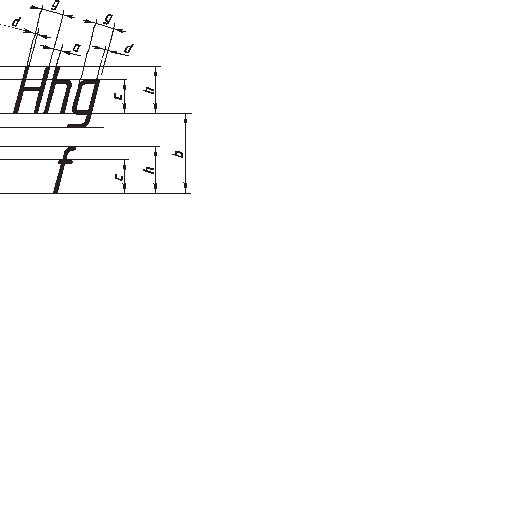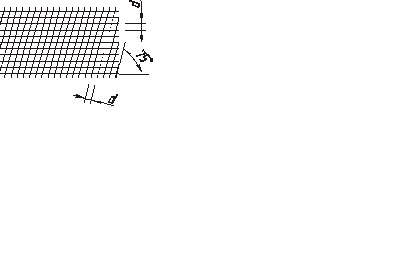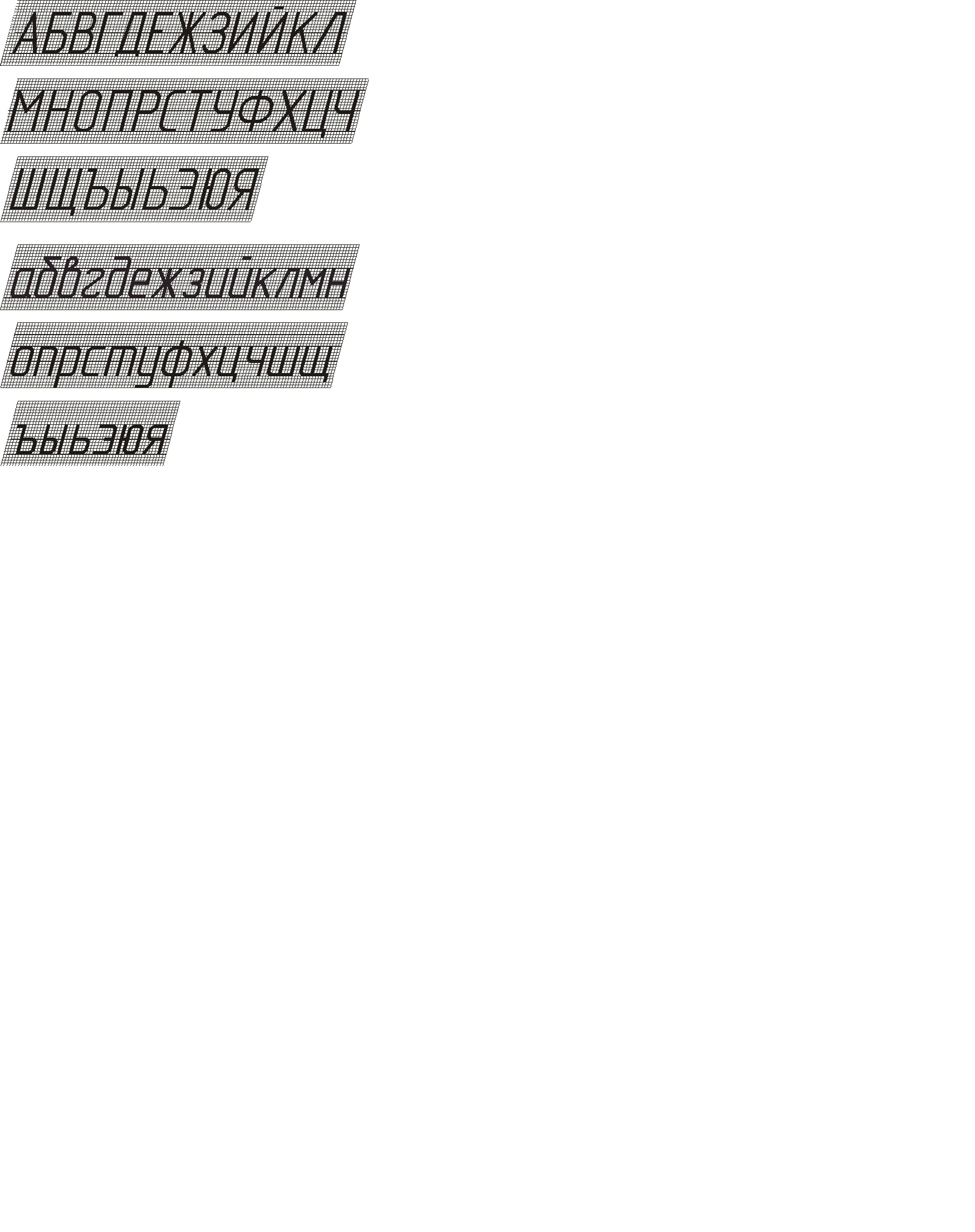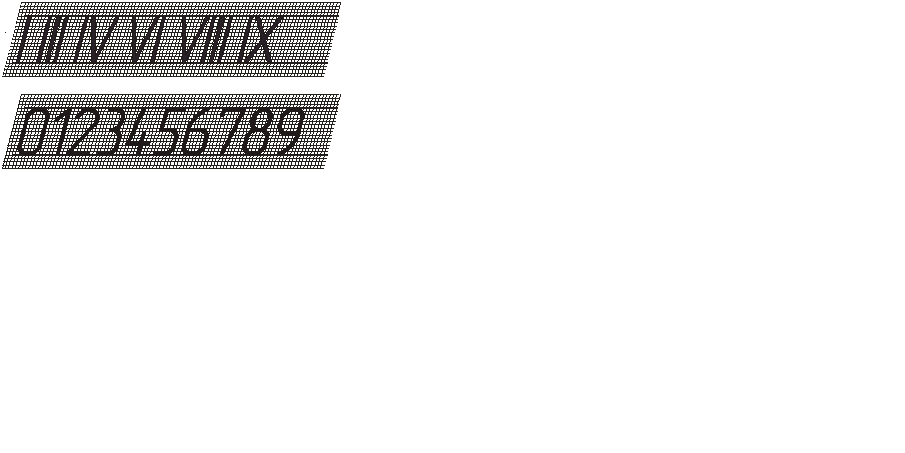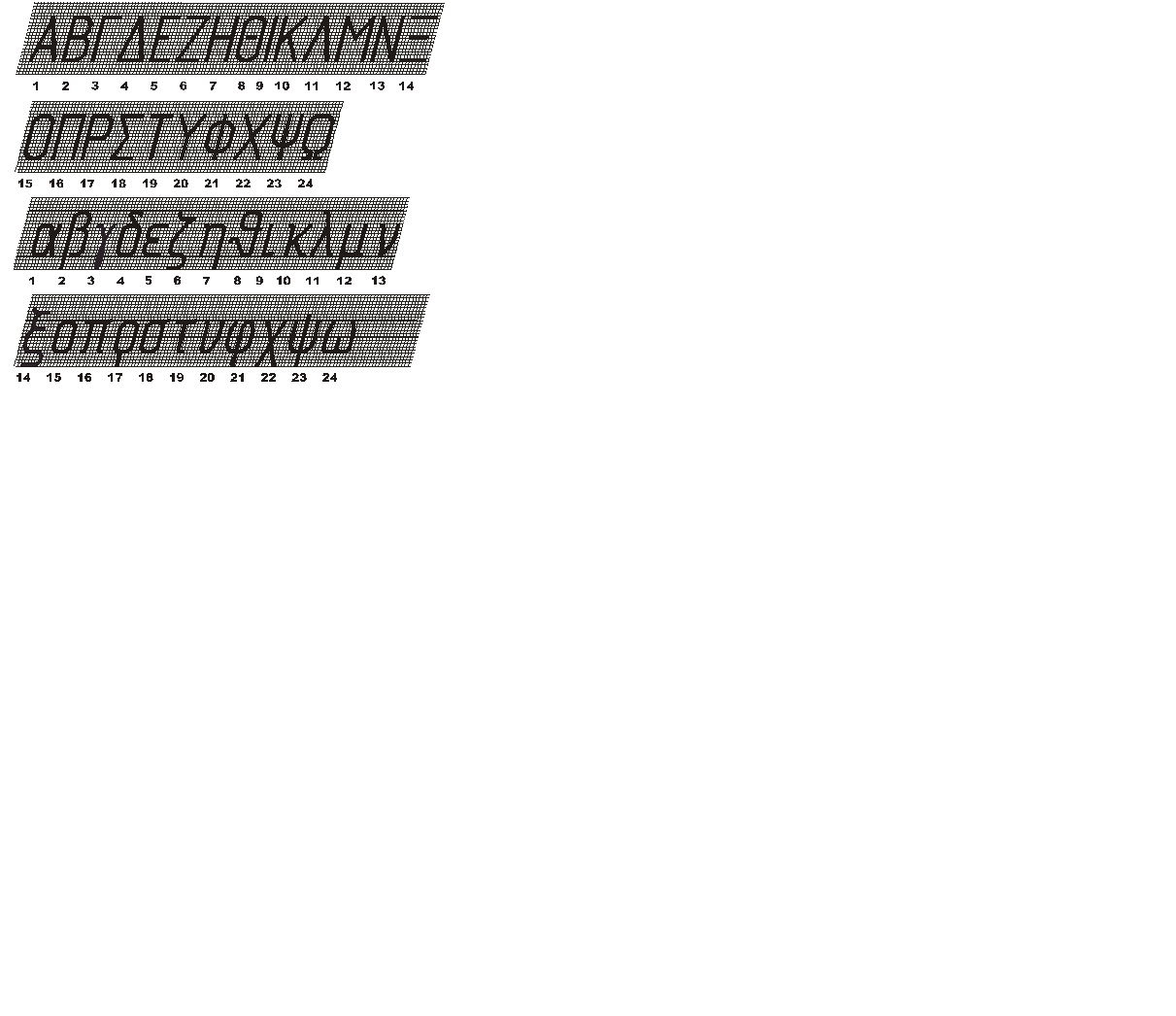
Шрифты чертежные. Чертежи выполняются на листах размерами, установленными ГОСТ 2
Все надписи на чертежах должны быть выполнены чертежным шрифтом. ГОСТ 2.304-81 устанавливает два типа шрифта: тип А и тип Б, с наклоном и без наклона. В настоящем пособии подробно рассмотрен шрифт тип А с наклоном 75° и параметрами, приведенными в таблице 4. Размер шрифта h – величина, определенная высотой прописных букв в миллиметрах. Высота прописных букв h измеряется перпендикулярно к основанию строки. Высота строчных букв c определяется из отношения их высоты (без отростков k) к размеру шрифта h, например, с = 7/10h (рисунки 1 и 2) Ширина буквы g – наибольшая ширина буквы, измеренная в соответствии с рисунками 1 и 2, определяется по отношению к размеру шрифта h, например, g=6/10h, или по отношению к толщине линии шрифта d, например, g = 6d. Толщина линии шрифта d – толщина, определяемая в зависимости от типа и высоты шрифта.
Рисунок 1
Вспомогательная сетка – сетка образованная вспомогательными линиями, в которые вписываются буквы. Шаг вспомогательных линий сетки определяется в зависимости от толщины линии шрифта d (рисунок 2).
Рисунок 2
Таблица 4 - Шрифт типа А (d= h/14) с наклоном
Примечания: 1 Расстояние a между буквами, соседние линии которых не параллельны между собой (например, ГА, АТ), может быть уменьшено наполовину, т.е. на толщину d линии шрифта. 2 Минимальным расстоянием между словами е, разделенными знаками препинания, является расстояние между знаком препинания и следующим за ним словом. 3 Устанавливаются следующие размеры шрифта: 2,5; 3,5; 5; 7; 10; 14; 20; 28; 40. 4 Предельные отклонения размеров букв и цифр +0,5 мм. Начертание букв и символов приведены на рисунках 3, 4, 5, 6, 7. РУССКИЙ АЛФАВИТ (КИРИЛЛИЦА)
Рисунок 3 ЛАТИНСКИЙ АЛФАВИТ
Рисунок 4
АРАБСКИЕ И РИМСКИЕ ЦИФРЫ
Рисунок 5 ГРЕЧЕСКИЙ АЛФАВИТ
Рисунок 6
ЗНАКИ
Рисунок 7 Наименования знаков приведены в таблице 5. Таблица 5 - Наименования знаков